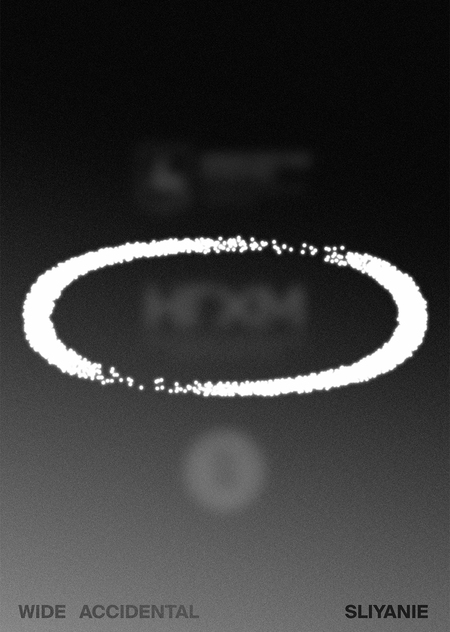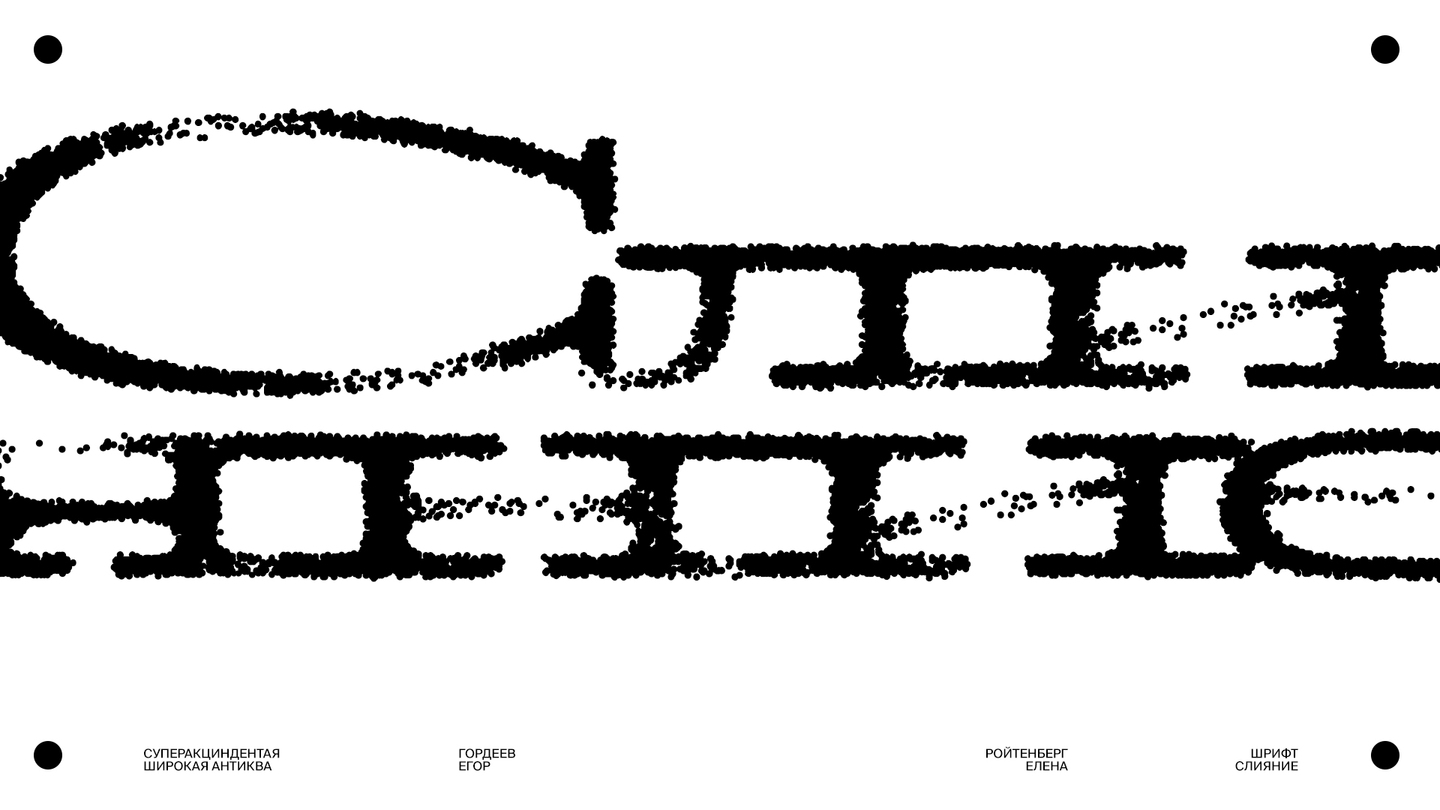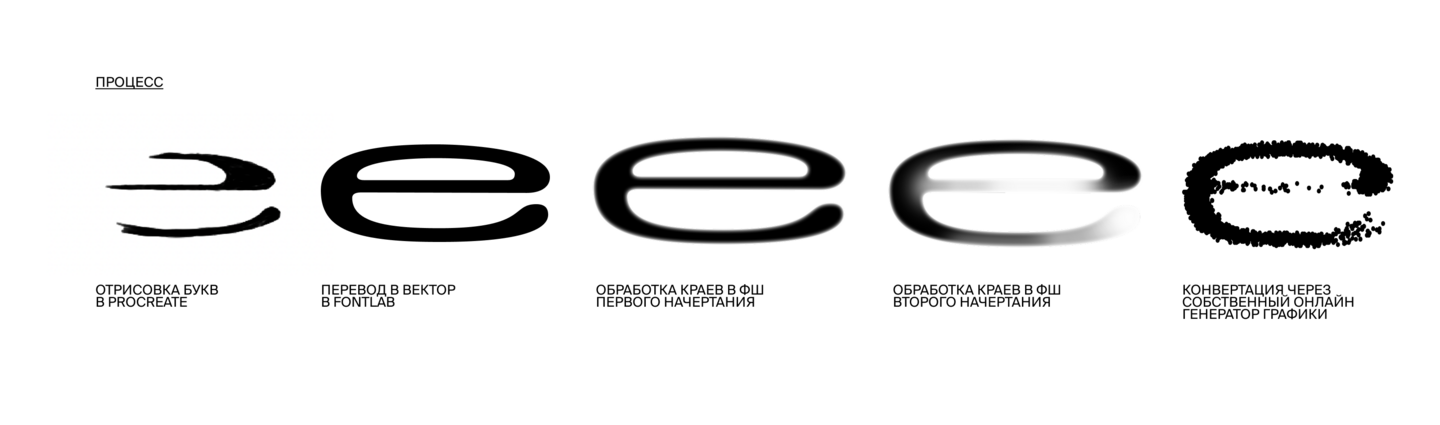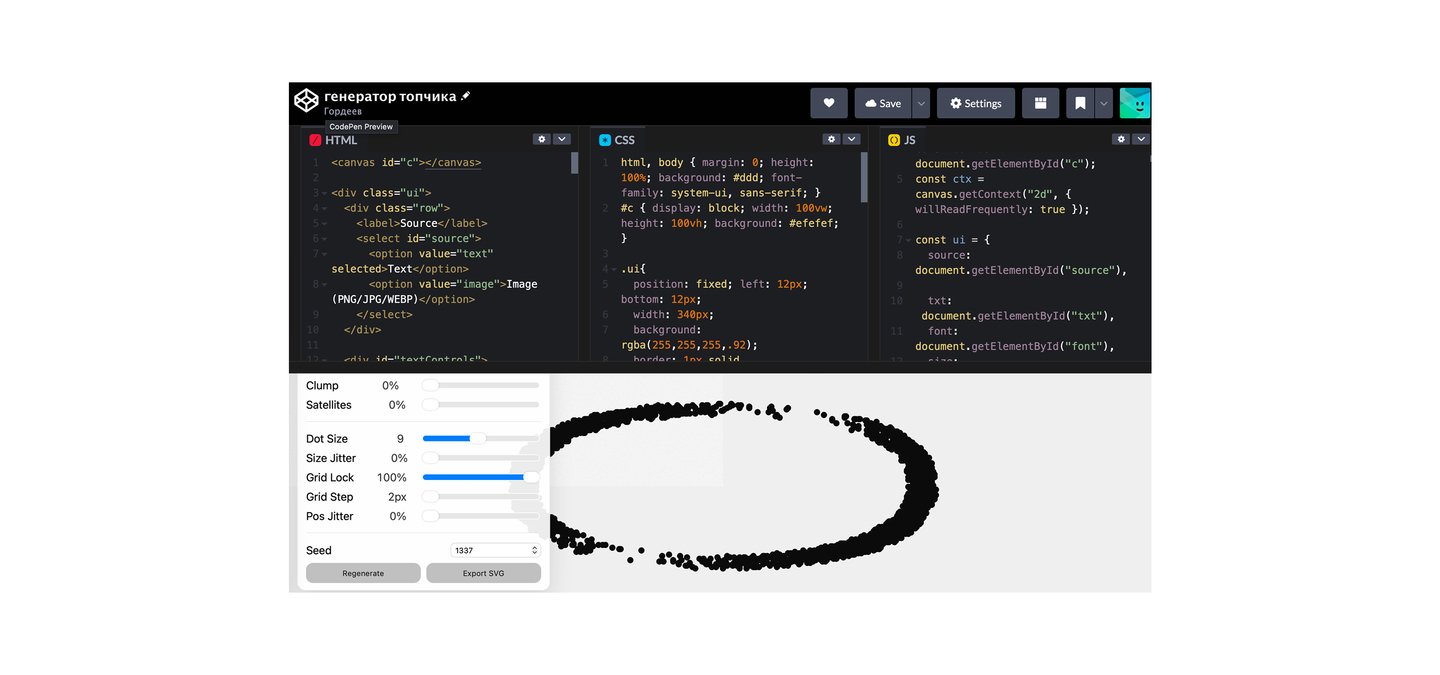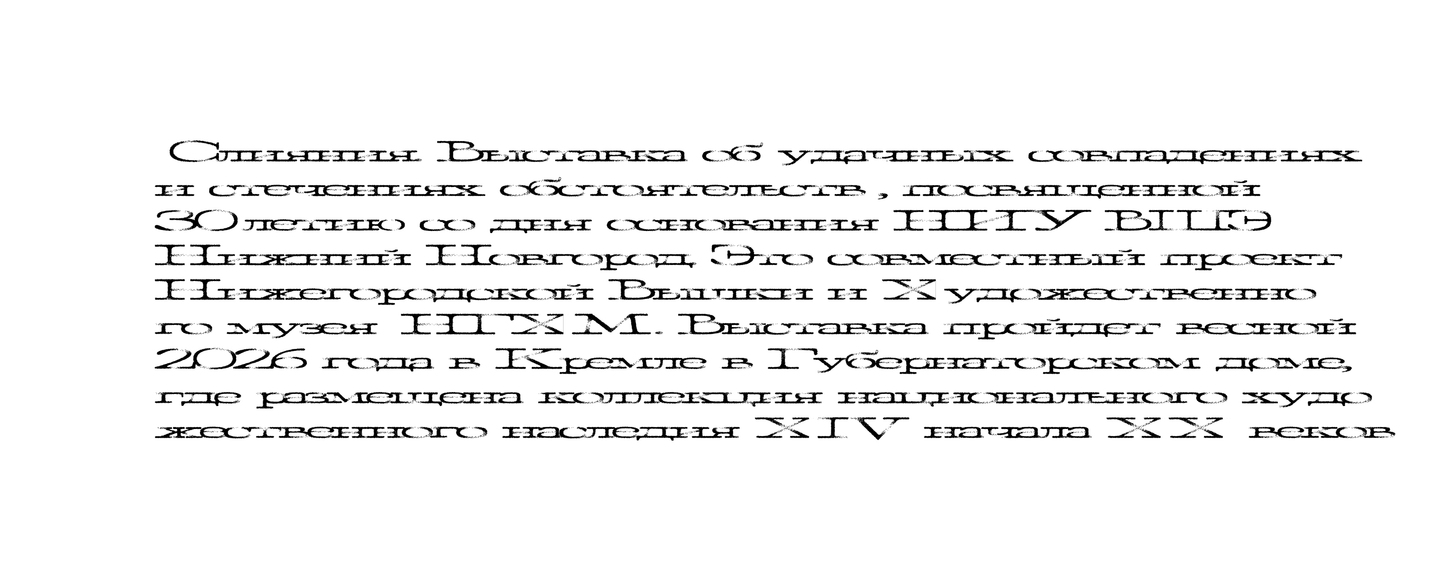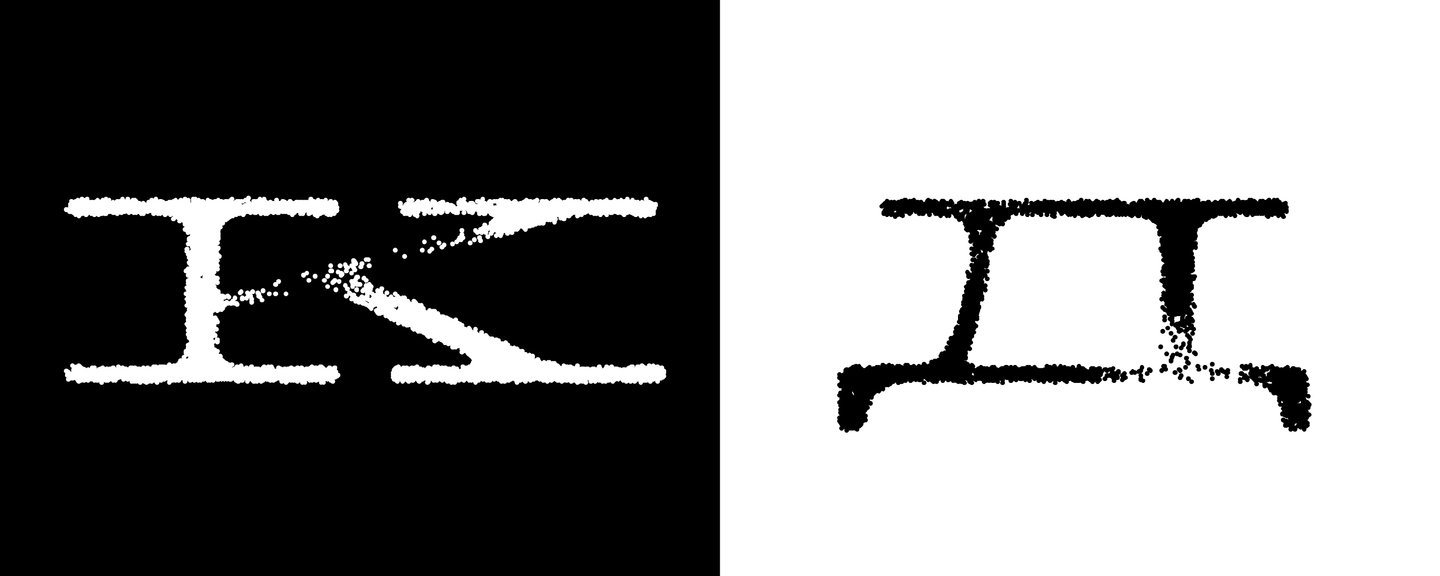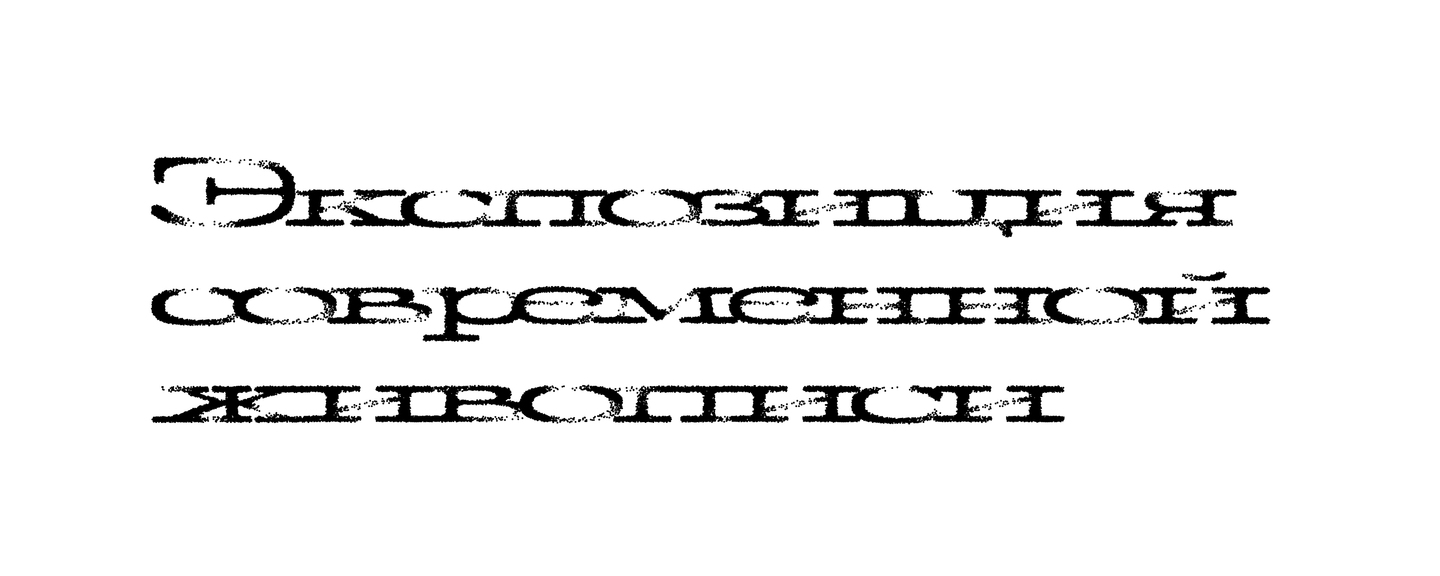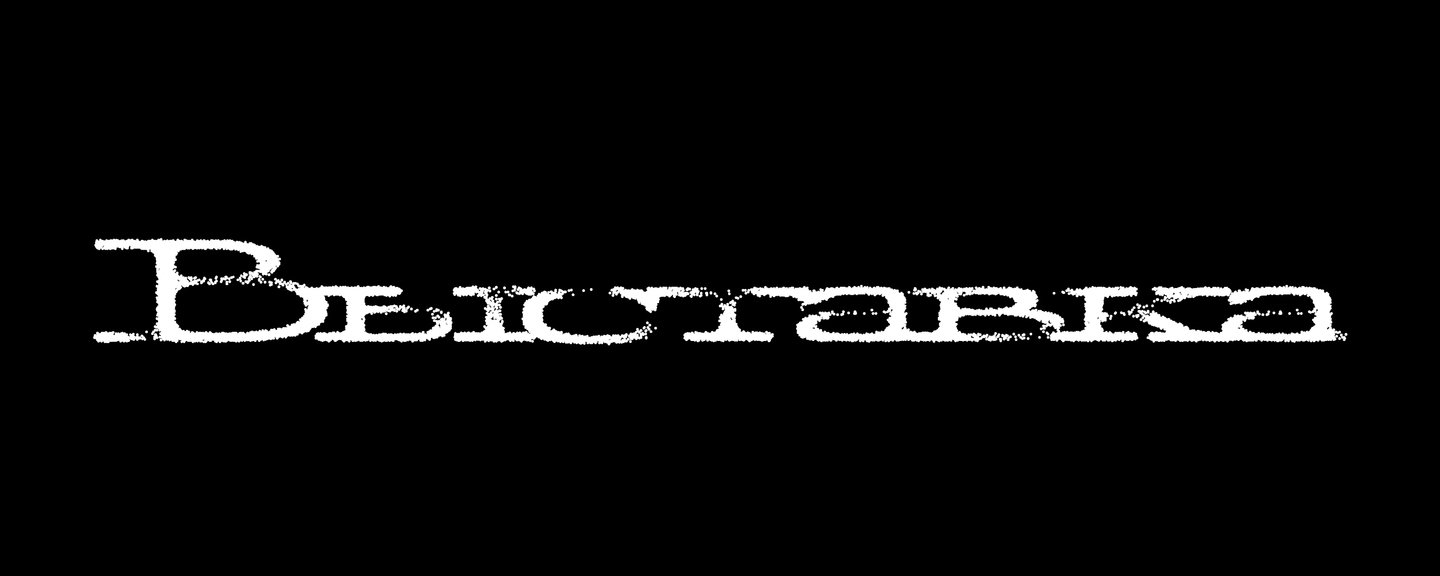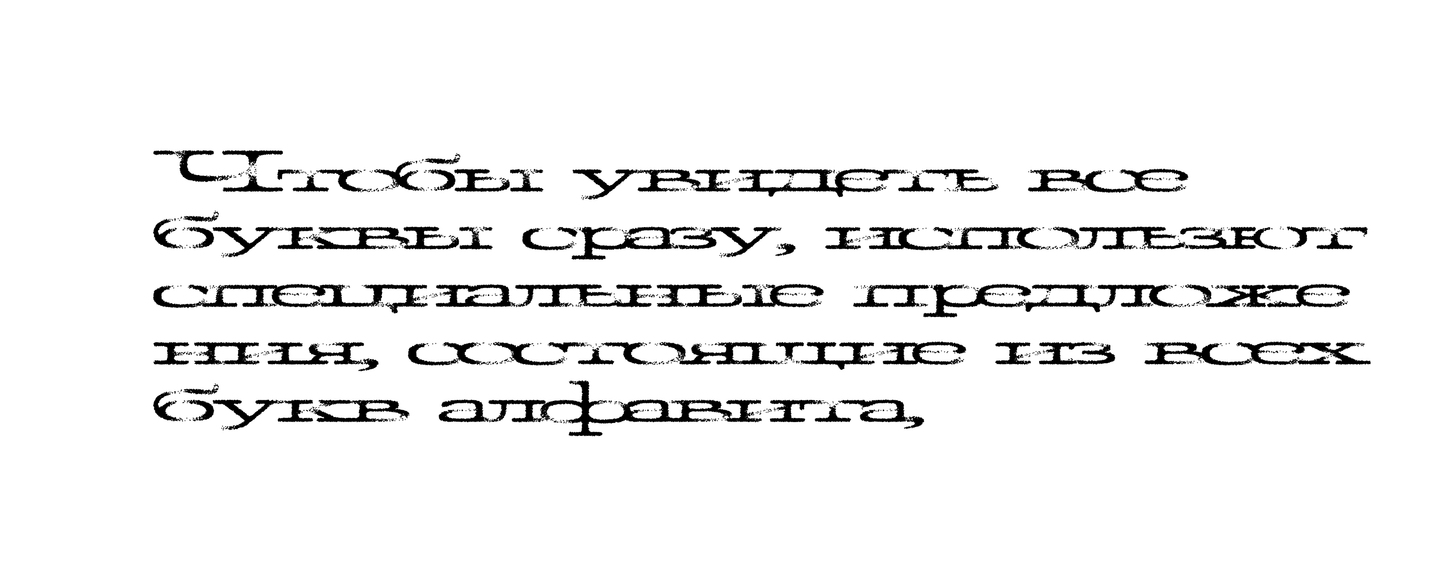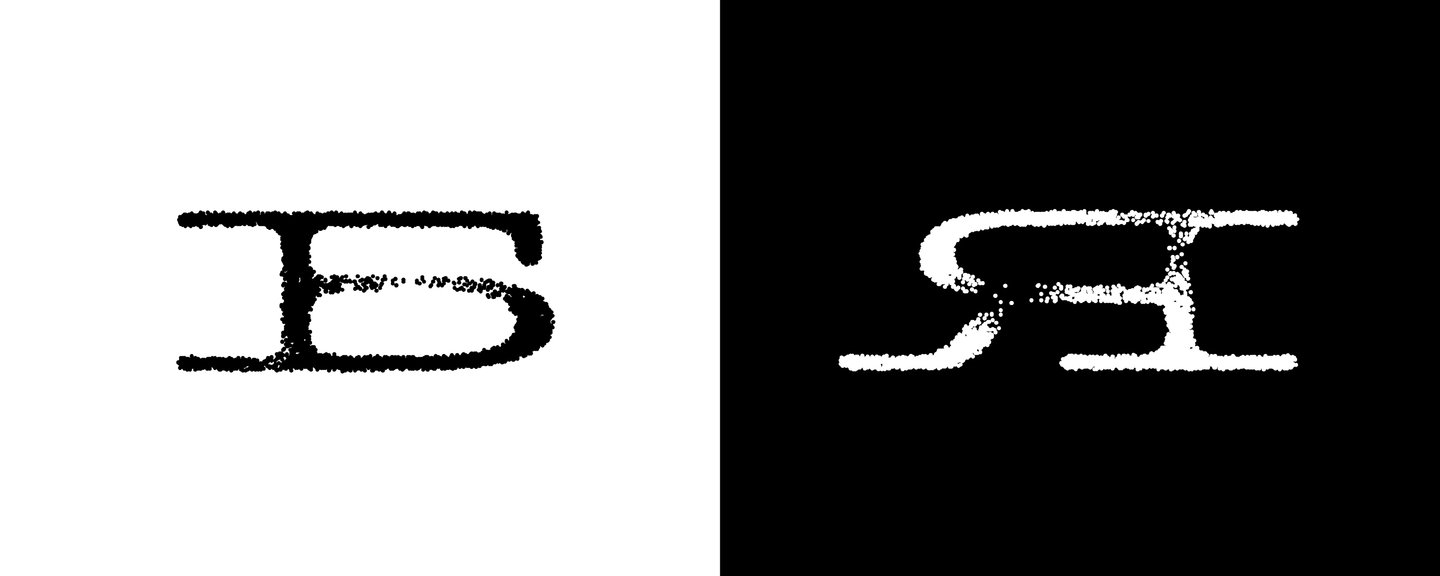
СЛИЯНИЯ
Шрифт вдохновлён главной идеей выставки «Слияния»: случайности, удачные встречи и стечения обстоятельств складываются во что-то большее — красивое, уникальное, неожиданно цельное
Для проекта был специально написан генератор векторной графики длинной 500+ строк.